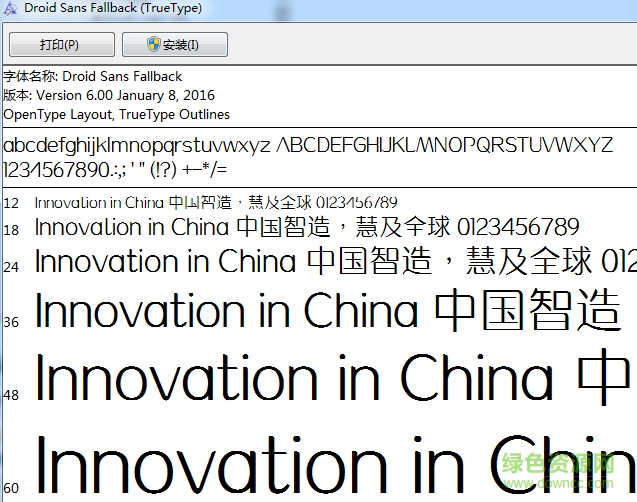
水云細(xì)水流個(gè)性字體
水云細(xì)水流字體是一款個(gè)性中文字體,字體非常纖細(xì)柔和,字體給人非常寧靜安逸的感覺,有喜歡的朋友可以來綠色資源網(wǎng)免費(fèi)下載使用!
水云細(xì)水流字體
水云細(xì)水流字體非常柔美,讓人看見這一字體就已經(jīng)沉浸其中了,感受字體的美,如果您需要的話,就趕快來綠色資源網(wǎng)下載吧!